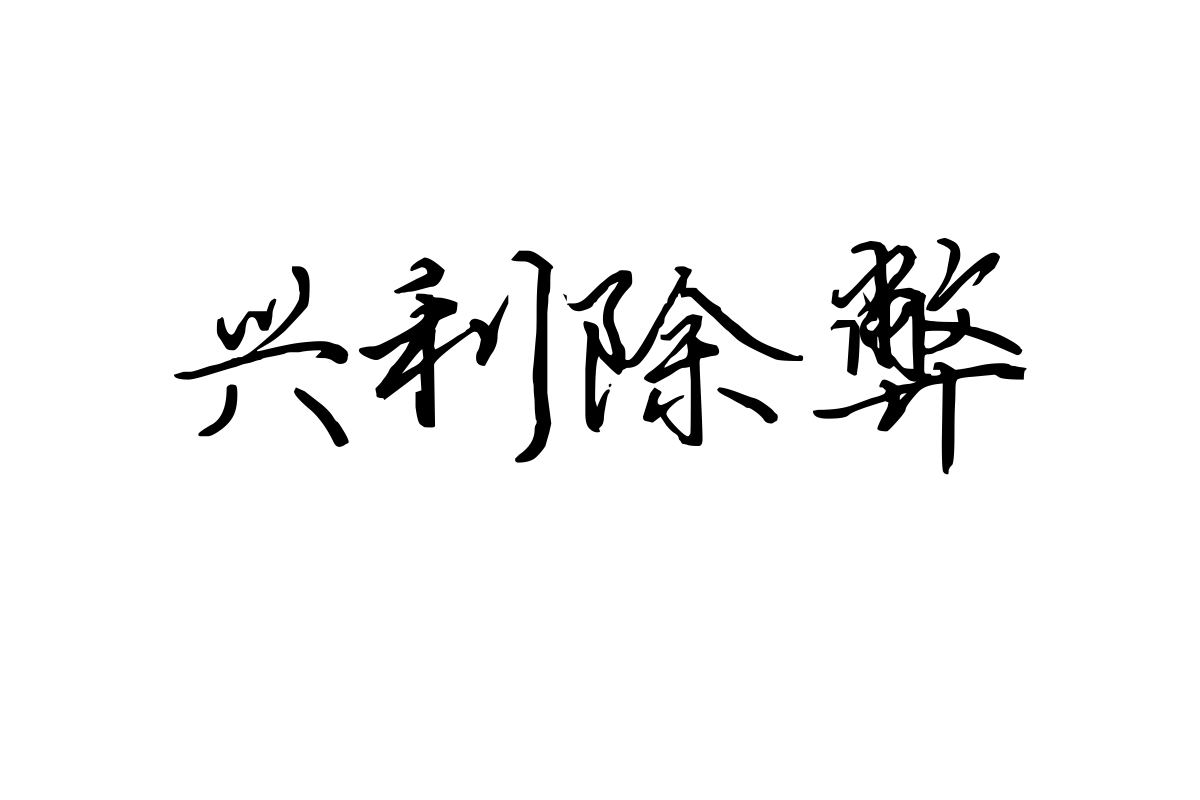
段宁硬笔行云体是一种特殊的汉字书写风格,它结合了传统书法的韵味和现代硬笔书写的特点。这种字体的特点是笔画流畅、结构紧凑、线条清晰,给人一种简洁而有力的感觉。
段宁硬笔行云体的笔画粗细变化丰富,既有粗犷豪放的一面,又有细腻柔和的一面。这种字体在书写时需要有一定的技巧和练习,但一旦掌握,就能展现出独特的艺术魅力。
段宁硬笔行云体适用于各种场合的书写,无论是日常笔记、工作报告还是艺术作品,都能展现出其独特的风格。同时,这种字体也适合初学者学习和练习,因为它的笔画结构简单明了,容易上手。